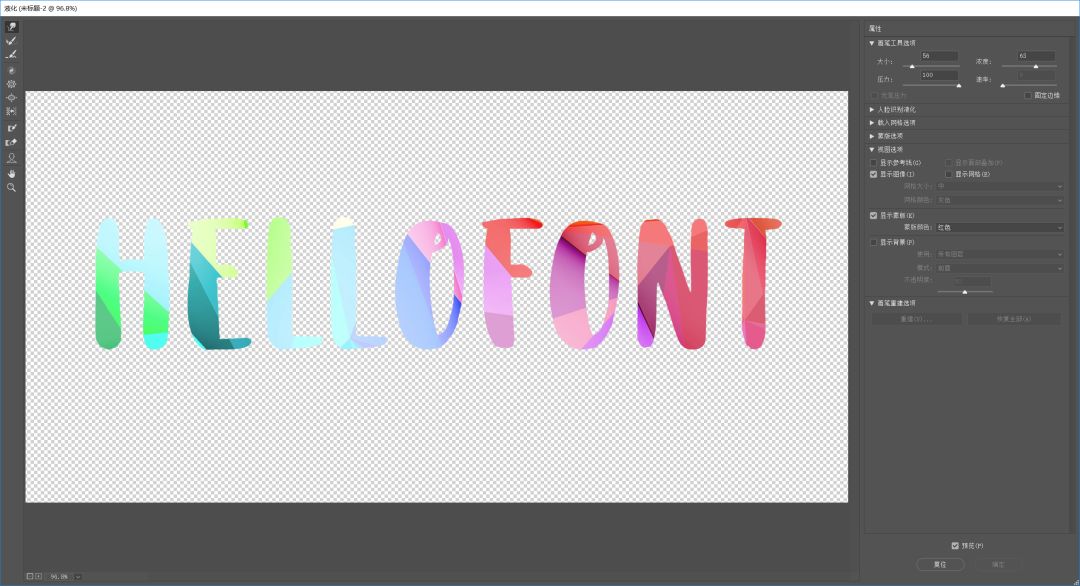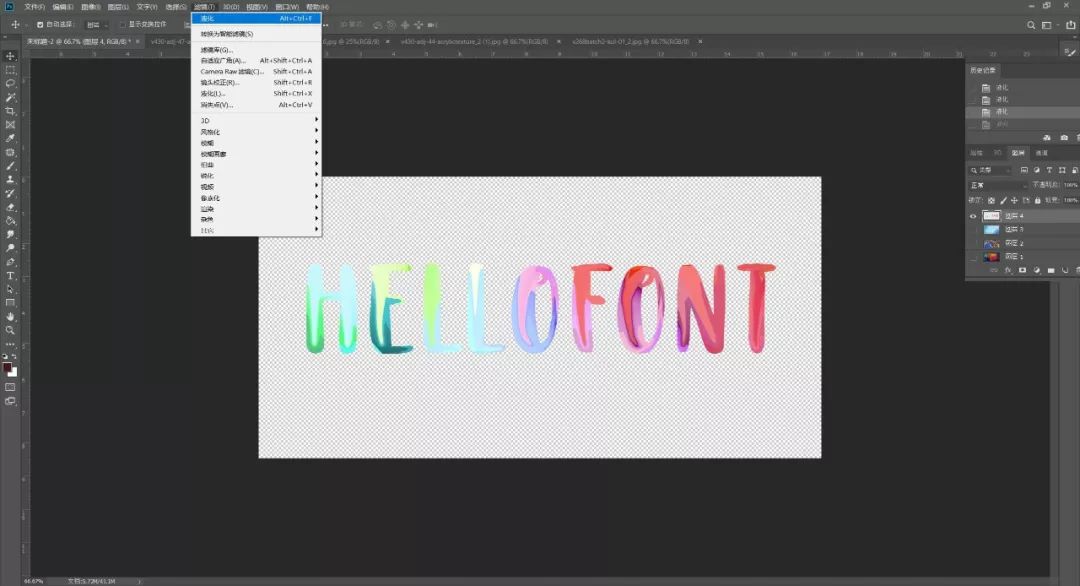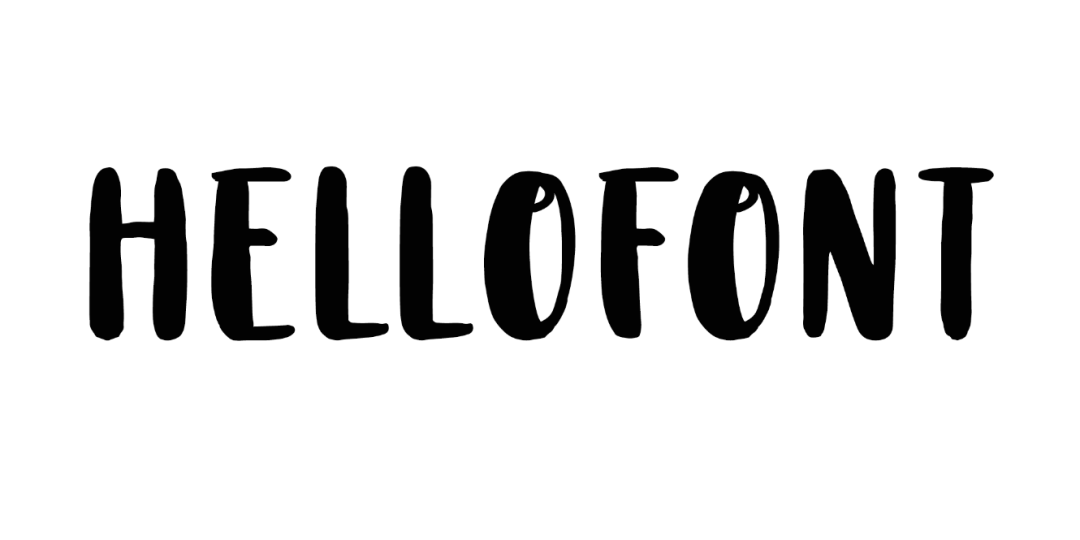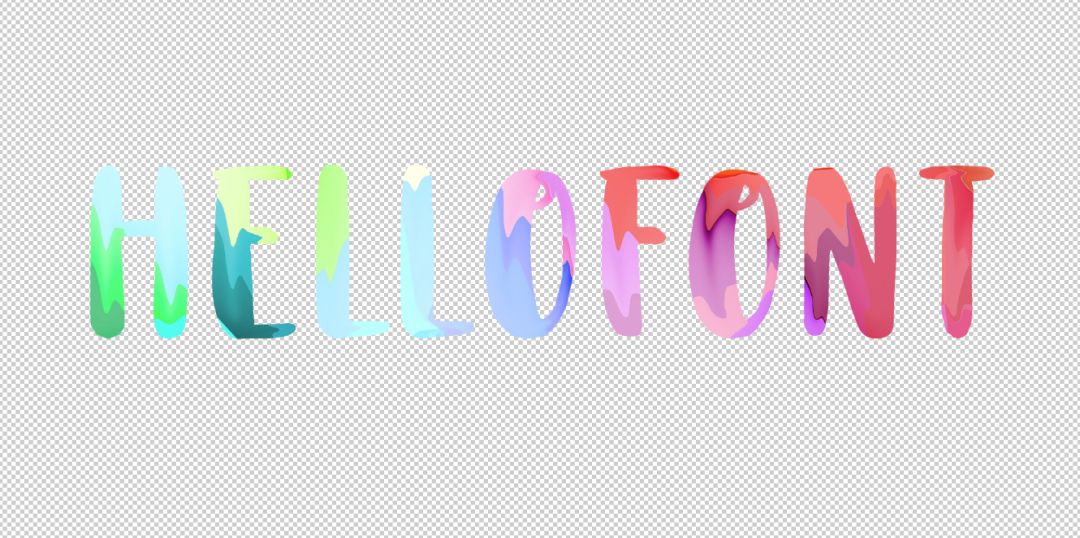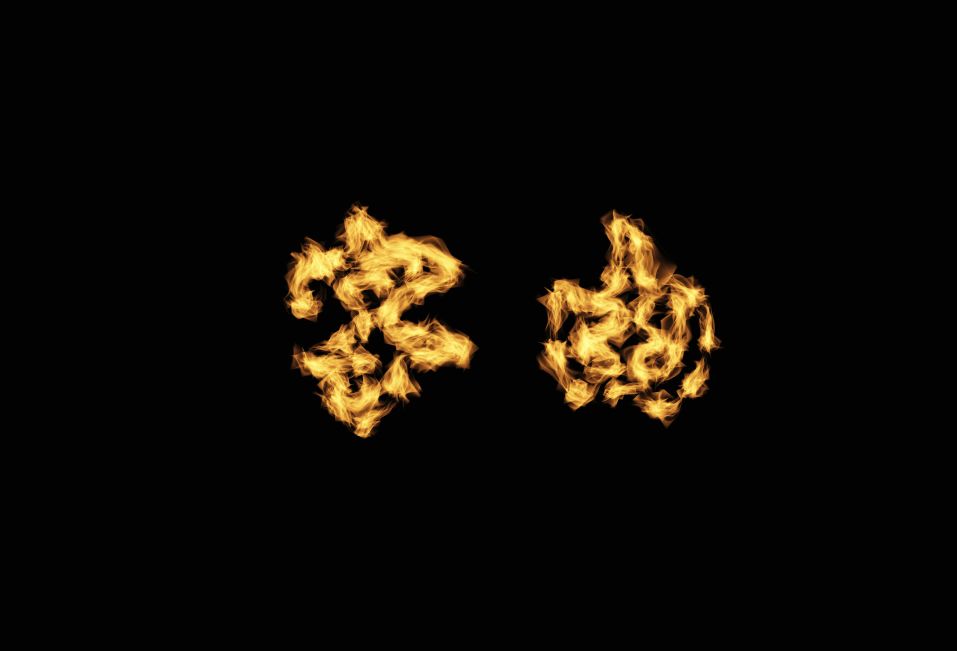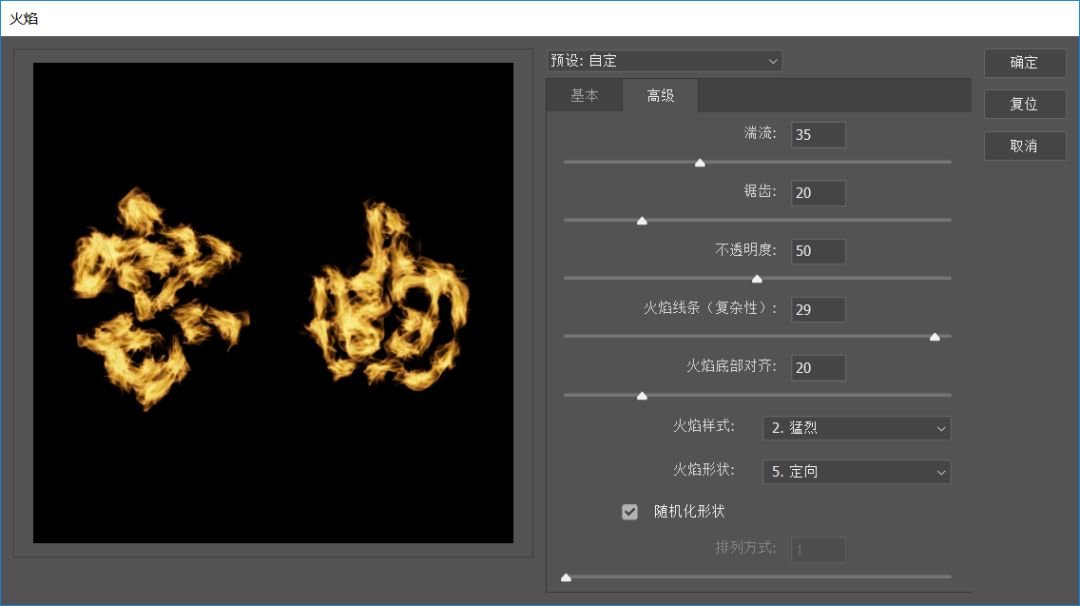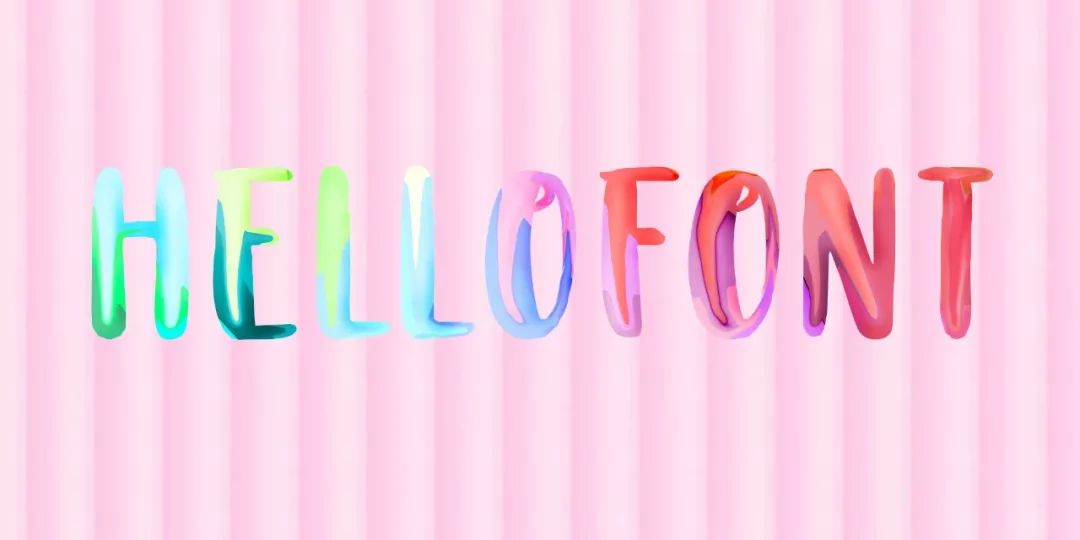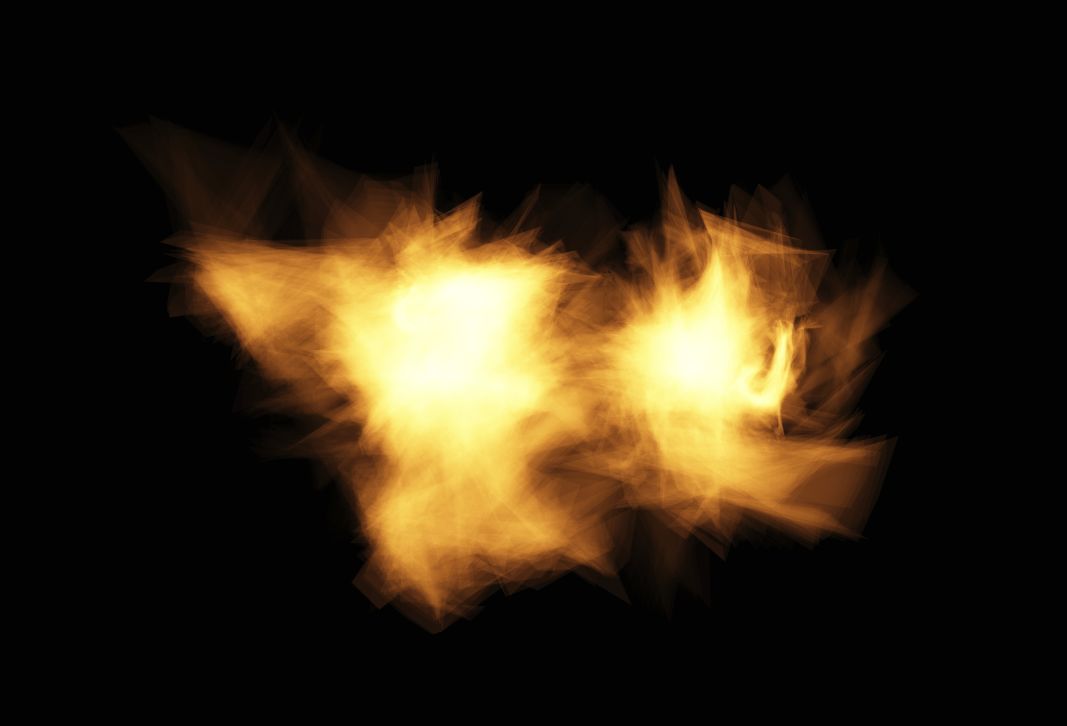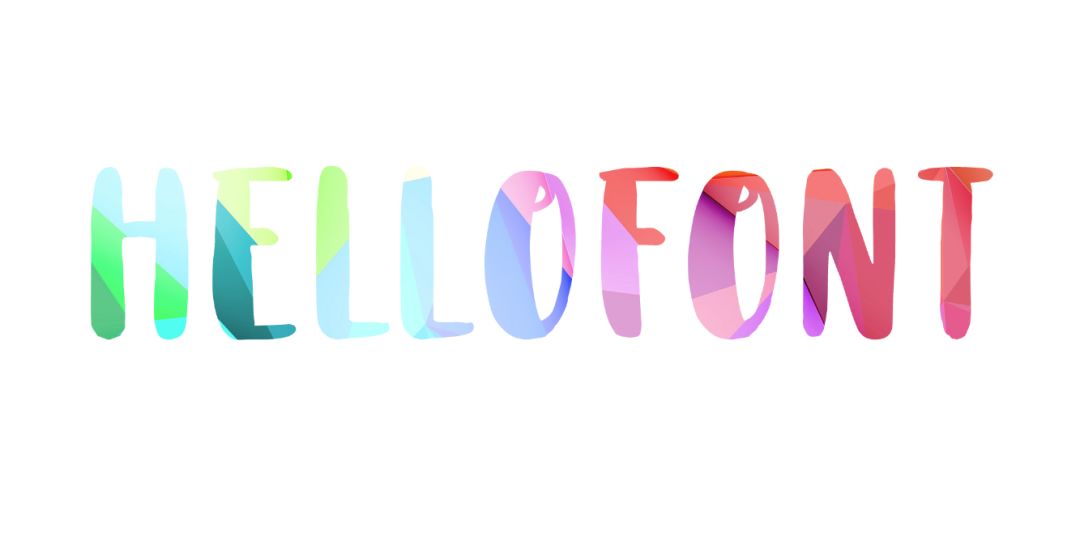
掌握这两个窍门,制作字体特效也可以“投机取巧”
今天依然是教你如何“投机取巧”,有些特效看起来很难,但其实是可以速成的,比如下面两款,跟上了啊~
彩绘油漆字
在不少电影中,都有那种把油漆打翻,碰撞在一起的桥段,呈现出艺术的美感,有没有想过在字上表现出来?说做就做,选择字由上的Mahoni Free Personal Use
再找一张纹理素材,颜色多一点,剪切蒙版~
除背景图外,合并图层,选择滤镜>液化。
把画笔调为字体大小,用向前变形工具,顺着“撸”一遍~
接下来选择最近的液化,再执行三四次。
加点阴影和高光,增加立体感,再换个背景,就哦了~
炫酷火焰字
最近“火”太火了,既然现实生活中干不过,那就在ps中做一个,还是在字由上选一款字体,汉仪李国兴行楷就不错~
右键创建工作路径,再复制一个图层,执行滤镜>渲染>火焰。
按照如下参数设置就可~
但是一定要有耐心,它经常玩你,不按常理出牌,哈哈哈~